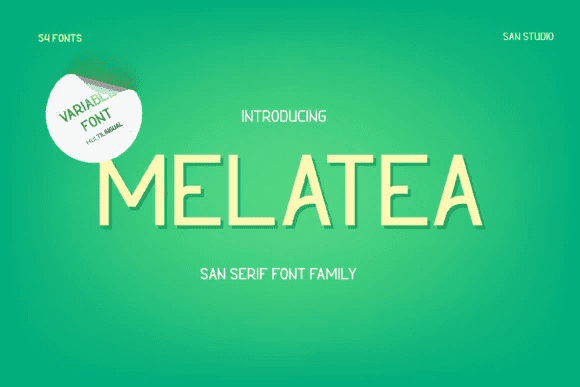
Название: Melatea Font (2021)
Melatea - это минимальный и аккуратный шрифт sans serif.
Его можно легко подобрать к невероятно большому набору проектов, поэтому добавьте его в свои творческие идеи и обратите внимание на то, как он их выделяет!